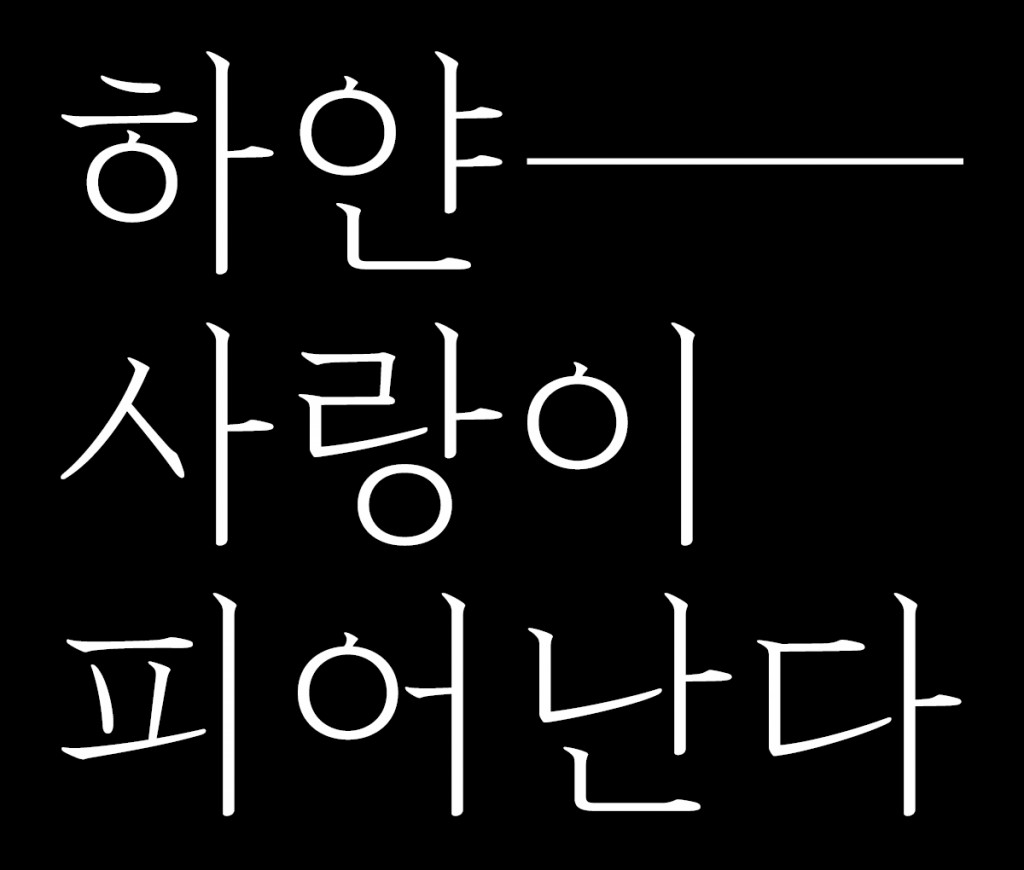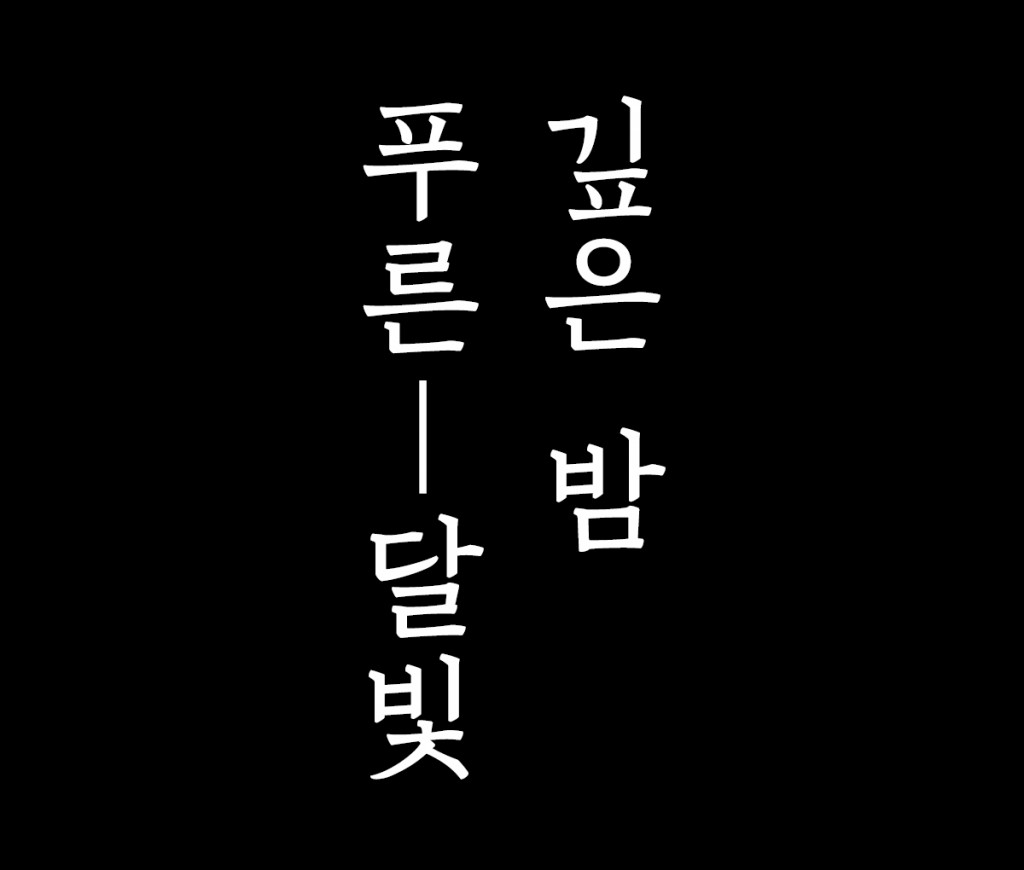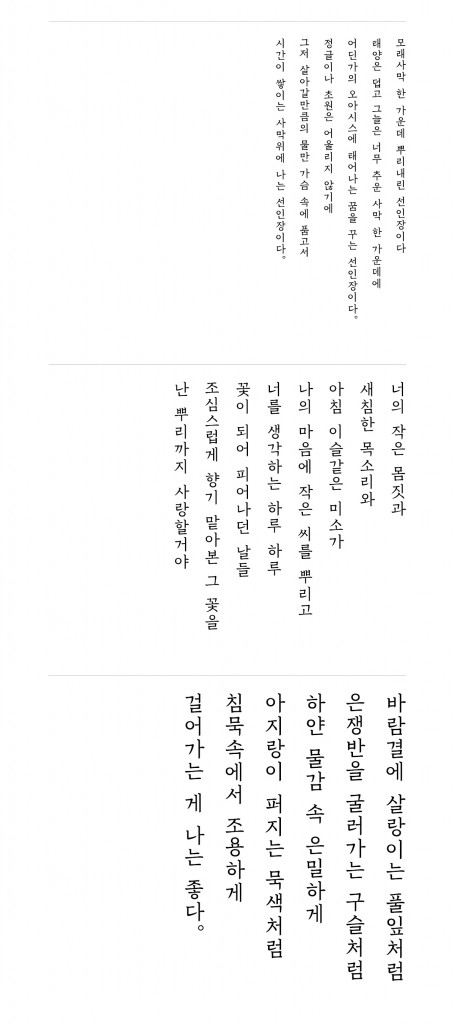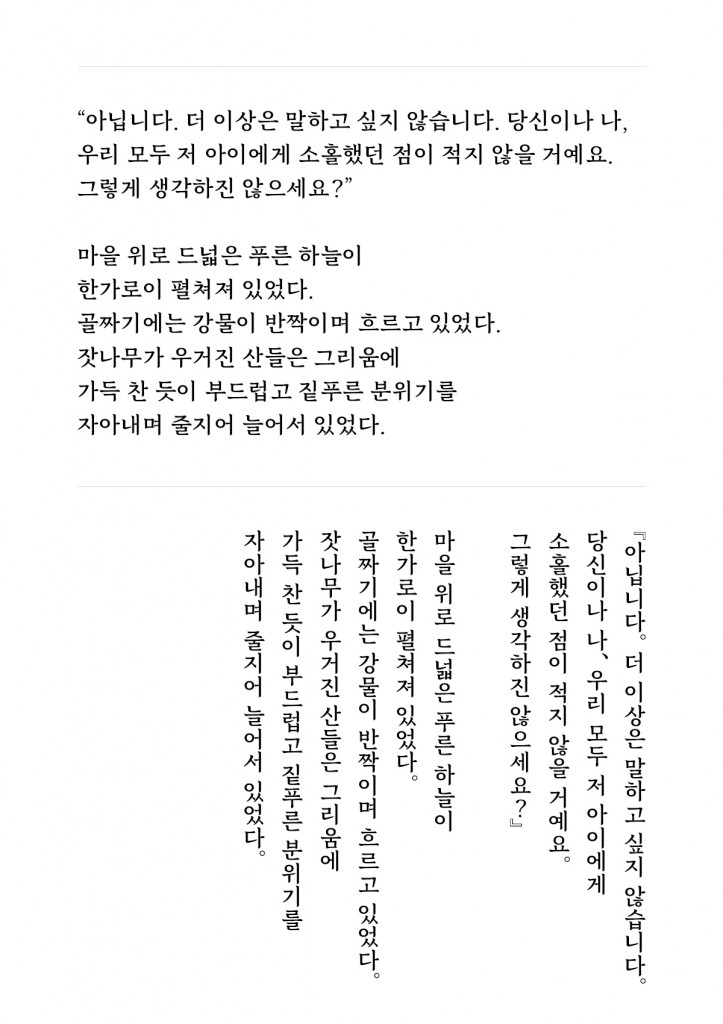
INTERVIEW. 채희준
새로움이나 트렌드를 추구하기 보다는 글자에서 느껴지는 감정과 형태의 상관관계를 생각한다는 서체 디자이너. 미세한 차이를 감지하고 연구하는 과정을 통해 글자를 만든다는 그를 만나 폰트와 폰트 디자인에 대한 생각을 들어보았다.
Q. 개인 디자이너기도 하지만 스튜디오로도 활동하는 것으로 알고 있다.
맞다. 포뮬러라는 디자인 스튜디오로 활동하고 있다. 스튜디오의 구성원은 두 명이다. 폰트를 만드는 채희준과 그래픽 디자인을 하는 신건모로 이루어져 있다. 서로 분야는 다르지만 상호보완적인 관계 속에서 시너지를 내고 있다.
Q. 처음부터 폰트 디자이너의 길을 걷겠다고 생각했었나?
물론 대학에서 한글타이포그래피를 전공하긴 했다. 그때 지도교수가 바람체로 유명한 이용제 디자이너였다. 하지만 실제로는 글자를 디자인 하는 것보다는 편집이나 그래픽 디자인 쪽에 조금 더 흥미를 느꼈다. 그래서 처음에는 ‘한글 디자인까지 잘하는 그래픽 디자이너’ 정도만 되어도 괜찮을 것 같았다. 그래픽 디자이너로서 한글 디자인까지 잘하면 큰 무기가 될 수 있으니까. 지금처럼 서체 한 벌을 만들게 될 것이라곤 전혀 생각치 못했다.
Q. 그럼 어떤 계기로 폰트 디자이너가 되기로 결심한건가?
2013년 졸업을 앞두고 졸업작품으로 서체를 제작했다. 그 글자가 바로 2016년 출시된 ‘청월’이다. 이렇게 하나의 폰트를 온전히 제작해 출시까지 하고 보니, 내게 어떤 취향 같은게 생기더라. 글자 디자인에 대한 견해랄까. 나중에는 ‘나는 이런 글자가 좋아’, ‘이런 질감의 글자도 만들어보고 싶다’와 같이 생각이 확장되기 시작했고, 이런 감정들을 바탕으로 자연스럽게 청월 이후의 글자 작업을 이어나가기 시작했다.
Q. 그럼 폰트 외에 다른 작업은 하지 않는건가?
청월을 출시하고 나서 독립적으로 활자를 제작하는 행위가 정말 직업이 될 수 있는지 확인하고 싶었다. 전력을 다했을 때 한 종의 폰트를 만들어내기까지 얼마의 시간이 필요한지 테스트해보고 싶기도 했다. 그래서 2017년 ‘청조’의 작업이 시작된 시점부터는 본격적으로 폰트만 디자인했다. 회사를 다니거나 아르바이트를 병행하지도 않았다. 글자를 그리는 일을 부업으로 하고 싶지 않았고, 치열하게 제작한 폰트를 통해 온전한 수익을 내보고 싶은 도전의식이 강했다. 그저 생존하는 정도가 아니라 다른 직업군과 비교해도 차이가 없을 정도의 수익을 내어야만 직업으로 여겨질 수 있을 것 같았다.
Q. 마음가짐이 정말 멋진 것 같다. 가만 보면 채희준의 폰트에서도 그런 결의가 느껴지는 것 같기도 하고.
가장 중요하게 생각하는 것이 내가 상상하던 느낌과 글자의 결과물이 일치하는가다. 느낌이라는 것이 추상적이고 막연한 감정이지만, 처음 상상했던 느낌을 정확하게 찾아내려고 노력해야 결과물의 완성도도 그만큼 높아질 수 있다고 생각한다. 기획 단계에서 머리로 글자를 상상하던 그 아우라가 결과물에서도 느껴지는지, 그것을 찾아가는 과정이 바로 완성도를 높이는 과정이다. 폰트 디자이너로서 그것이 결의라면 결의일지도.
Q. 공개한 세 가지 폰트들은 처음의 그 느낌이 잘 반영되었다고 생각하나?
아무래도 ‘초설’이 그 막연한 느낌을 찾아내려 가장 노력한 글자가 아닐까 싶다. 글자적인 기획과 문법으로 접근했던 청월, 청조와는 다르게 초설은 오직 ‘첫눈’의 느낌을 담는 것에 집중했다. 초설이 갖고 있는 기본 구조는 일반적으로 통용되고 있는 바탕체를 충실히 따랐지만, 세부적인 표현은 그저 추상적인 감상으로만 디자인했다. 그렇기 때문에 글자적인 논법보다는 나만의 ‘주관적인 느낌’에 더 충실했다고 볼 수 있다. 쉽게 말해 청월과 청조가 “어떤 질감으로 이 글자를 나타낼까?”를 고민했다면, 초설은 “이 글자에 온도가 있다면 어느 정도의 온도일까?”를 고민했다고 보면 된다.
Q. 글자에 그런 느낌을 담는다는 것이 참 신기하다. 그것도 한글이 가진 매력 중 하나일까?
한글 디자인은 아직 다양한 형태를 모색중인 단계이고, 양식도 정립되지 않은 시점인 것 같다. 그렇기 때문에 다양한 조형에 대한 시도를 해볼 여지가 많은 시기다. 아무래도 이 부분이 수익을 내기도 힘들고 작업도 지루한 한글 디자인 시장에 그나마 활기를 불어넣는 지점이지 않을까? 최근 첫 작품으로 세로쓰기 전용 폰트를 제작하는 사람들이 생겨나는 것도 비슷한 이유라고 생각한다. 1,000개의 가로쓰기 폰트들 사이를 뚫고 1,001번 째 가로쓰기 폰트를 만드는 일보다 10개의 세로쓰기 폰트 중 11번 째 세로쓰기 폰트를 만드는게 더 흥미로울 수 있다는 생각이 든다. 한글의 매력이 바로 이런 부분이다. 물론 한글이든 라틴이든 각자의 의미를 찾아내는 것이 가장 중요하겠지만.
Q. 각자의 의미라는 것에 대해 좀 더 이야기해달라.
글자는 상품이기 때문에 시장성도 중요하지만 일단은 자신이 좋아하는 형태를 찾아서 그려보는 것이 더 중요한 것 같다. 독립적으로 작업하는 폰트 디자이너는 더욱 그렇다. 폰트는 상당히 긴 시간을 요구하는 분야라서 능동적인 태도로 작업을 해야 하는데, 본인이 그리고 있는 글자가 만족감이 높아야만 글자 한 벌을 완성할 수 있기 때문이다. 학생이면 졸업전시 때문에 억지로 작업할 수도 있고, 회사에 소속된 디자이너라면 월급을 받아야 하니까 억지로 작업하게 될 수도 있다. 하지만 독립적으로 글자를 그리는 디자이너는 수동적인 태도로는 글자를 완성하기가 매우 힘들다. 그래서 두고두고 파일을 열어보고 능동적으로 작업하기 위해서는 일단 자기가 좋아하는 형태부터 찾아서 그려나가는 것이 시작이라고 생각한다. 마음에 들고 좋아하는 감정이 생기면 계속 열어보게 될 테니까.
Q. 듣고 보니 폰트 디자이너에게는 인내와 주관이 중요한 덕목인 것 같다. 스스로 보기엔 어떤가?
확실히 어떤 일을 진행할 때 경쟁, 기한, 재촉 같은 요소들을 원동력으로 삼는 사람이라면 독립적으로 폰트를 제작하기에 불리한 것 같다. 반대로 강제성이 동반되지 않고도 능동적으로 작업을 완결시킬 수 있는 사람이라면 유리한 편이고. 레터링이나 전용서체를 의뢰받아서 진행하는 것은 다른 분야의 디자이너들과 큰 차이가 없다. 반면에 독립적으로 폰트를 작업하는 일은 작업에 대한 보상을 예상하지 못하는 상황에서 오롯이 본인의 의지로 성취해내야 하는 일이기 때문에, 어려우면서 값진 일이라고 생각한다. 나 스스로를 돌아보면 타인과 경쟁하는 일 보다는 나 자신을 이겨내는 일에 더 동기부여가 되는 편이다보니 이 일이 잘 맞는 것 같다.
Q. 폰트 디자인을 업으로 삼으면서 부딪히는 어려움은 없나?
작업에 긴 시간이 소요되고, 폰트를 출시한다고 해서 시장의 반응이 바로 오는 것도 아니다보니 보상이 보장되어 있지 않은 점? 남들이 보기에는 아무 일도 하지 않는 것처럼 보이기도 하고. 사회적인 시선과 불안한 감정들을 삼켜내며 온전히 내 의지와 다짐으로 긴 시간을 달려야 끝을 볼 수 있다는 것이 어려운 부분이다.
Q. 그럼에도 불구하고 이 일을 계속하는 이유는 뭘까? 폰트 디자이너로서의 삶에는 어떤 매력이 있다고 보는가?
하나부터 열까지 내 의지로 이루어낸다는 것이야 말로 큰 장점이지 않을까? 사소한 차이를 위해 전체를 다시 수정할 배짱도, 논리적 모순이나 형태적 조악함을 인정하고 포기할 용기도, 책임감 있게 프로젝트를 완수할 끈기까지 모든 것이 나 자신에게 달려있다는 점은 다시 생각해도 큰 매력이다.
Q. 이야기를 들어보니 앞으로 나올 폰트들이 더욱 기대된다. 마지막으로 지켜나가고 싶은 가치나 방향이 있다면?
계속해서 내가 궁금한 형태를 실험하고, 내가 갖고 싶은 글자를 만들어내고 싶다. 그리고 내가 떠올렸던 그 느낌들, 내가 그렸던 감정들을 사용자들에게도 고스란히 전달할 수 있도록 집중할 예정이다.